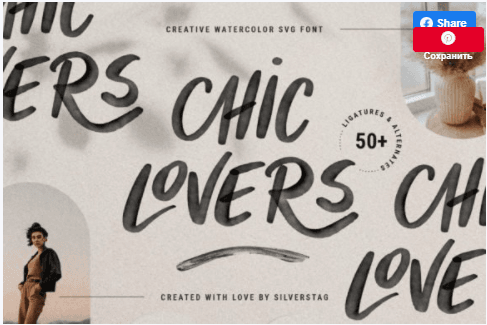
Chic Lovers Font
Chic Lovers - это стильный дисплейный шрифт с начесом, отличающийся идеальной модностью. Независимо от того, используете ли вы его для создания предметов, цифрового дизайна, презентаций или изготовления поздравительных открыток, он идеален!